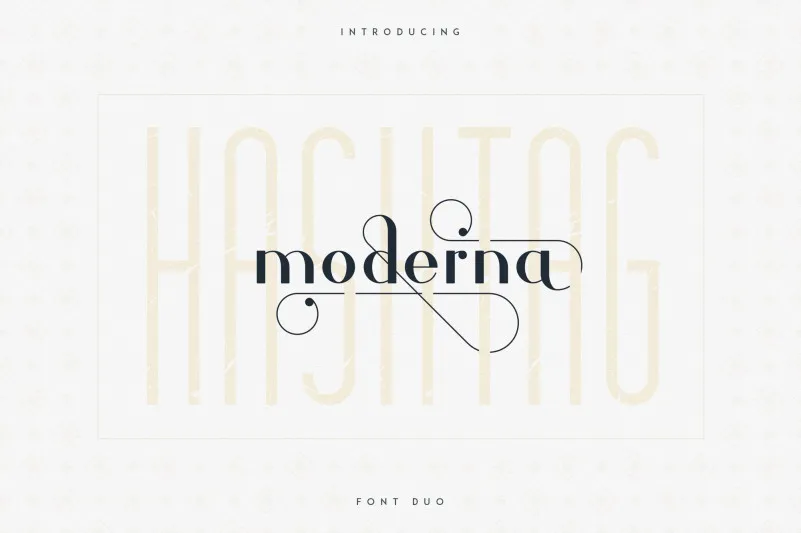
Hashtag Moderna – Duo Font é uma fonte moderna e elegante que oferece quatro estilos distintos com opções de alternativas abundantes, ligaturas, padrões e suporte a múltiplas línguas. Esta fonte pode ser facilmente adaptada para diversos tamanhos e formatos, tornando-a ideal para aplicações tanto em grandes como pequenos detalhes. Seja você um designer gráfico ou uma editora digital, esta Duo Font de Hashtag Moderna é perfeitamente adequada para criar designs modernos e sofisticados com um toque atraente de personalidade. Com sua versatilidade única, Hashtag Moderna – Duo Font é uma excelente escolha para quem busca estilo e simplicidade em cada projeto gráfico que cria.